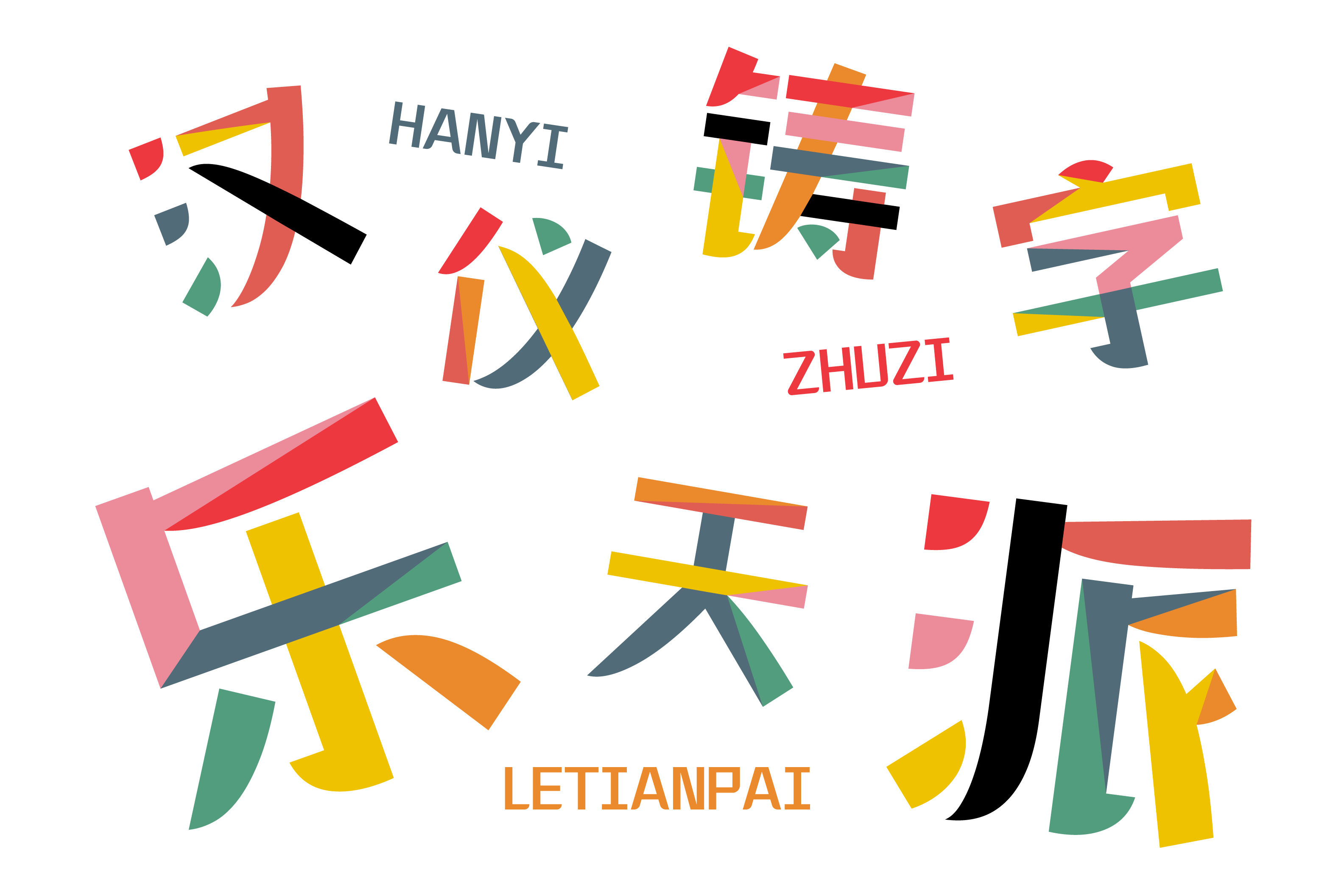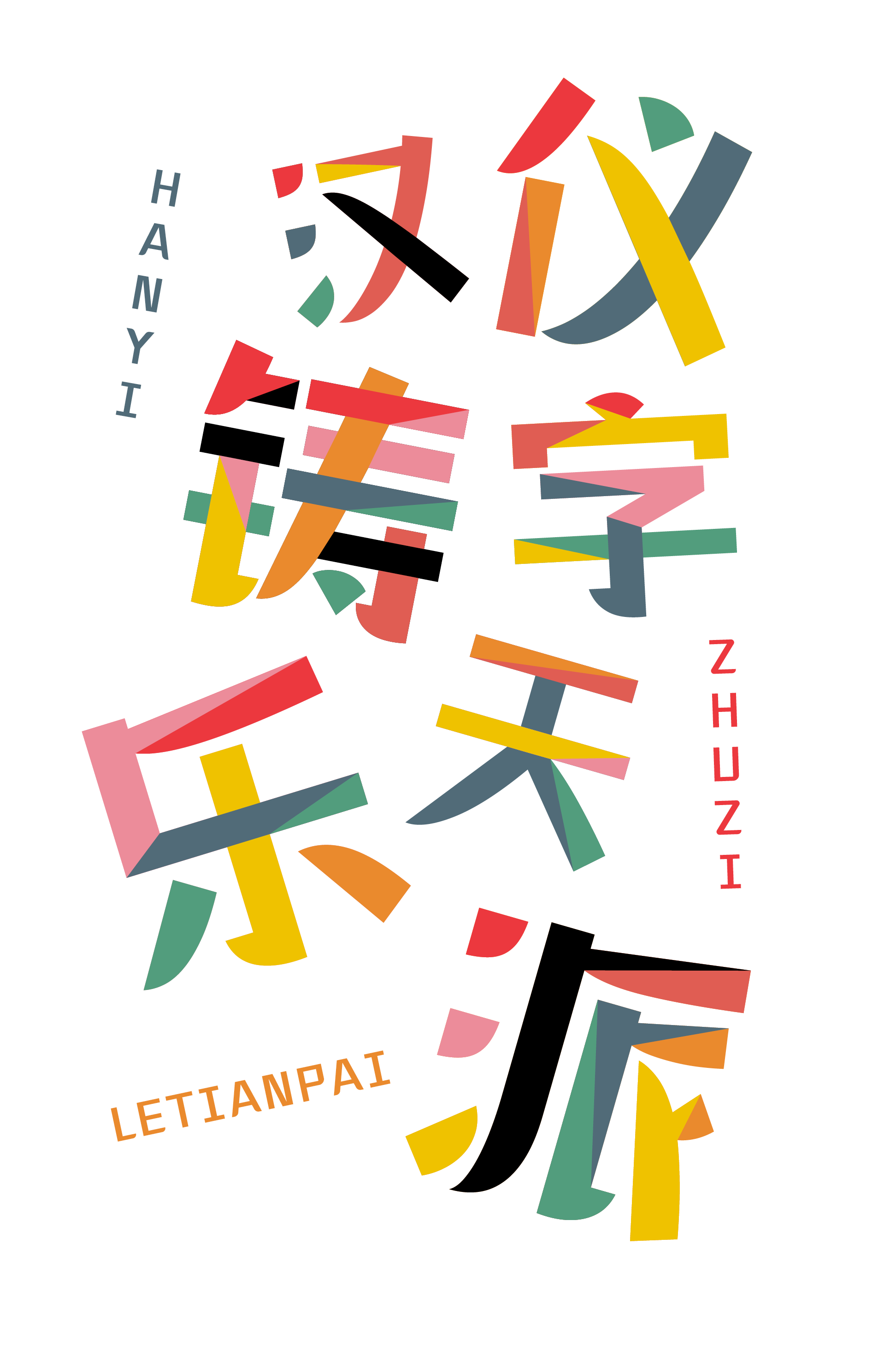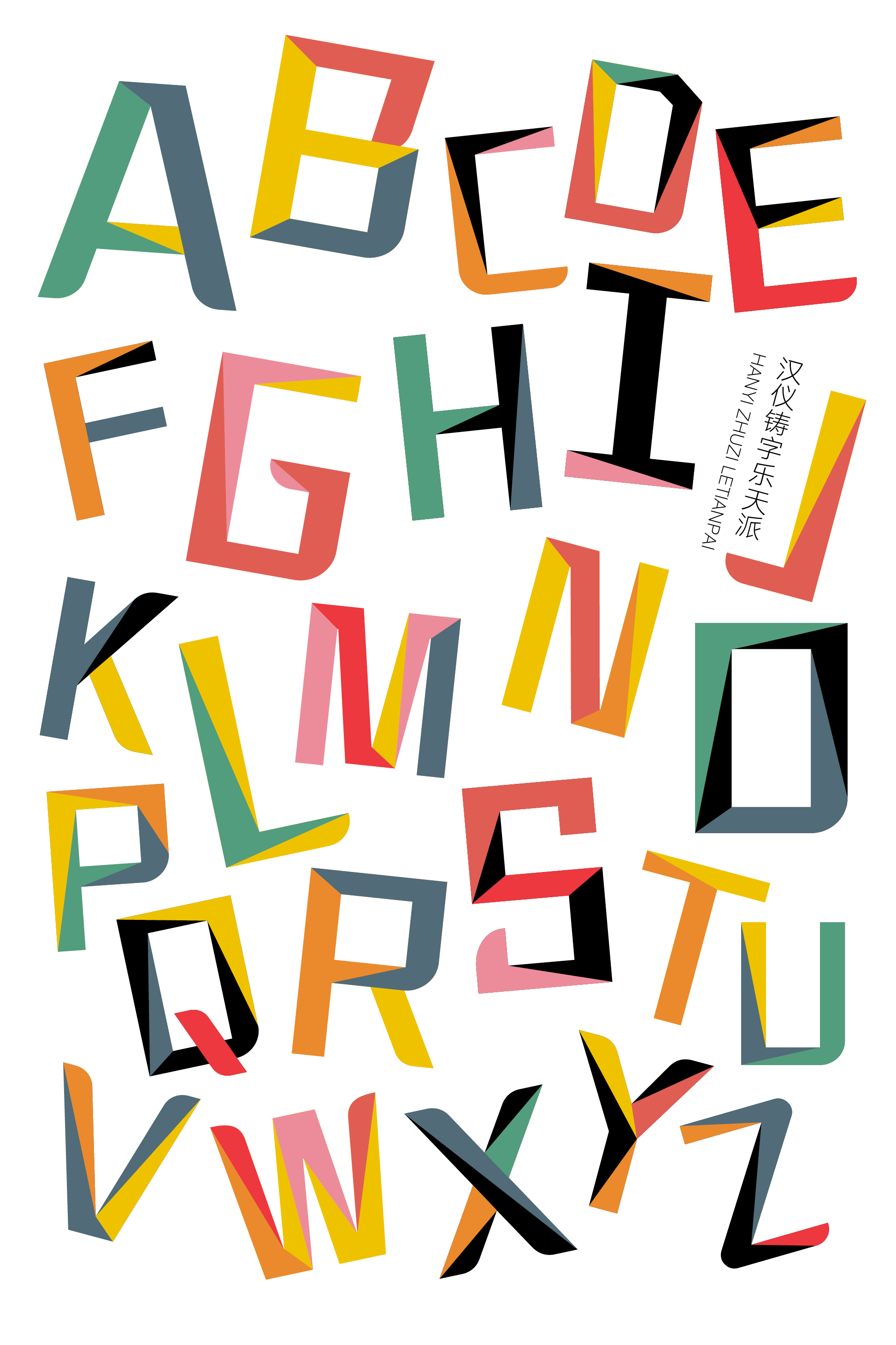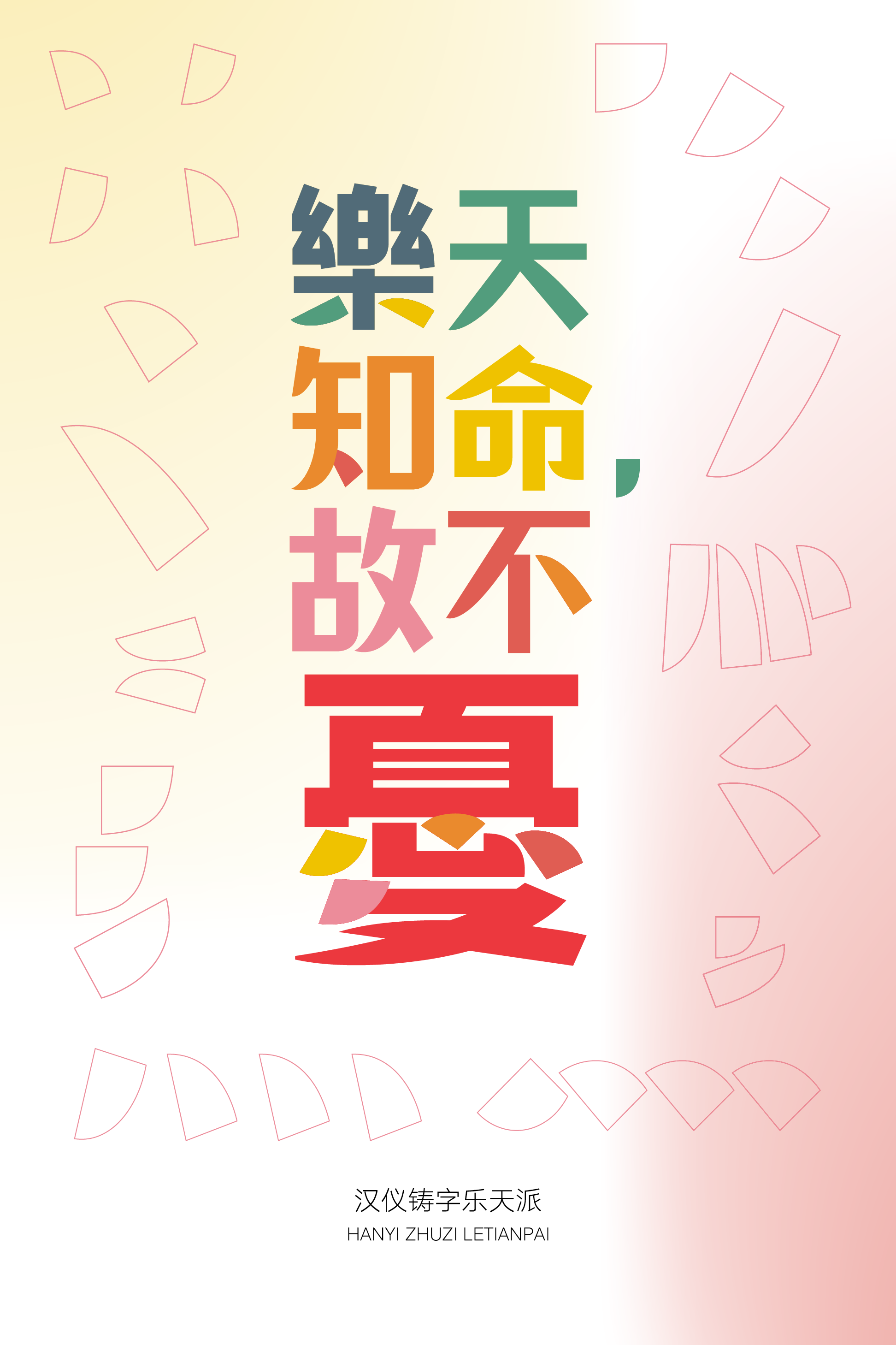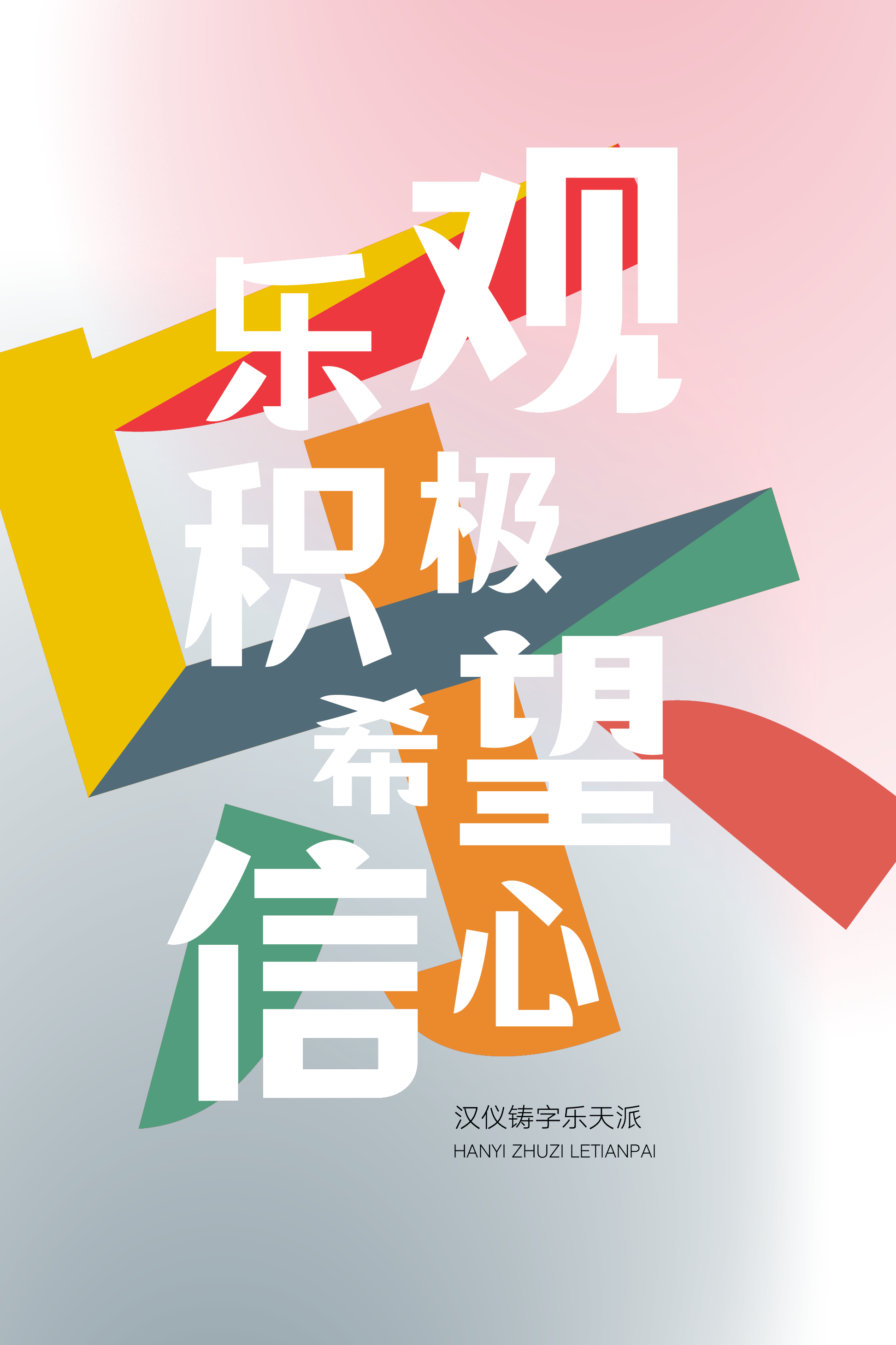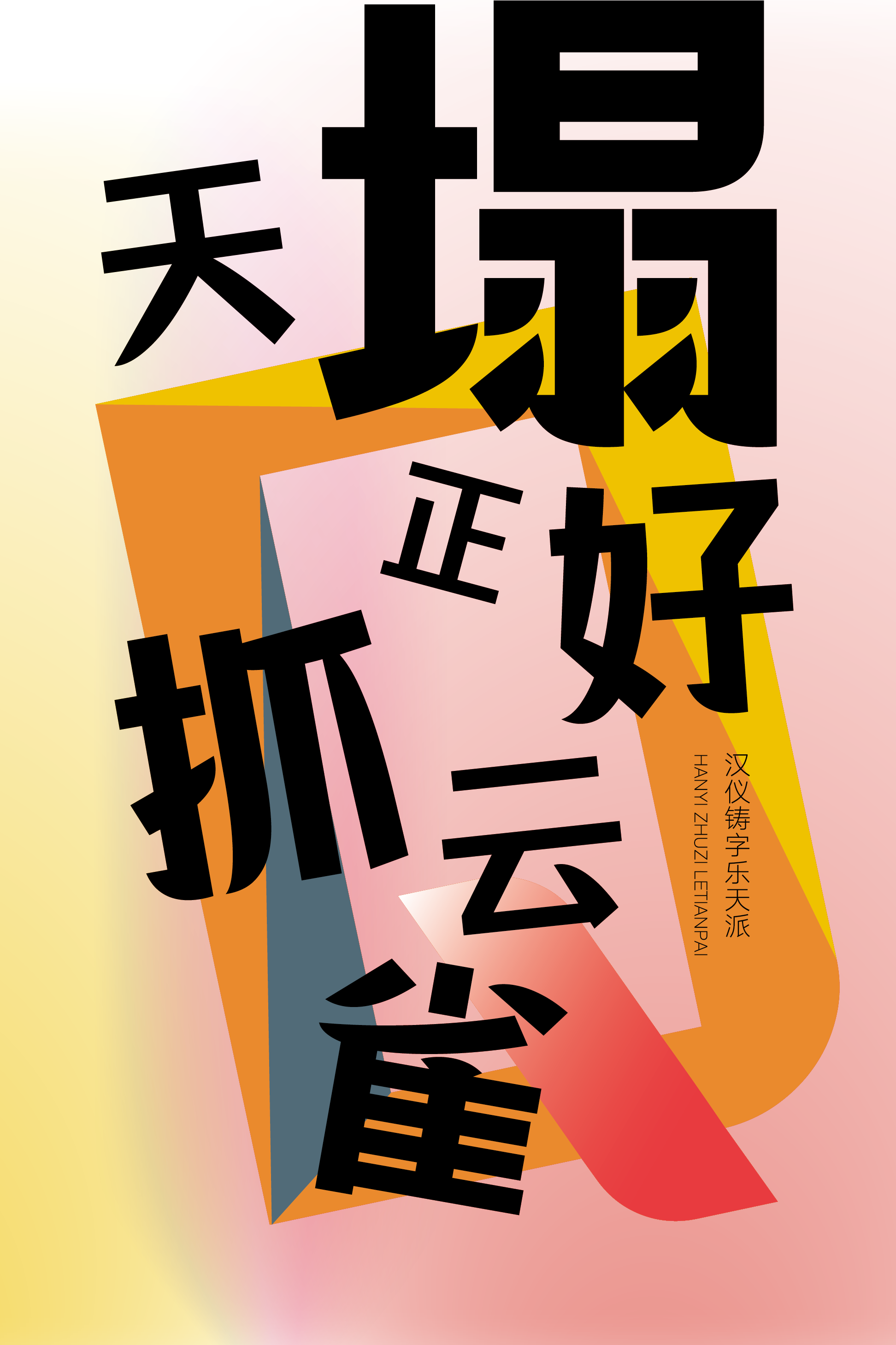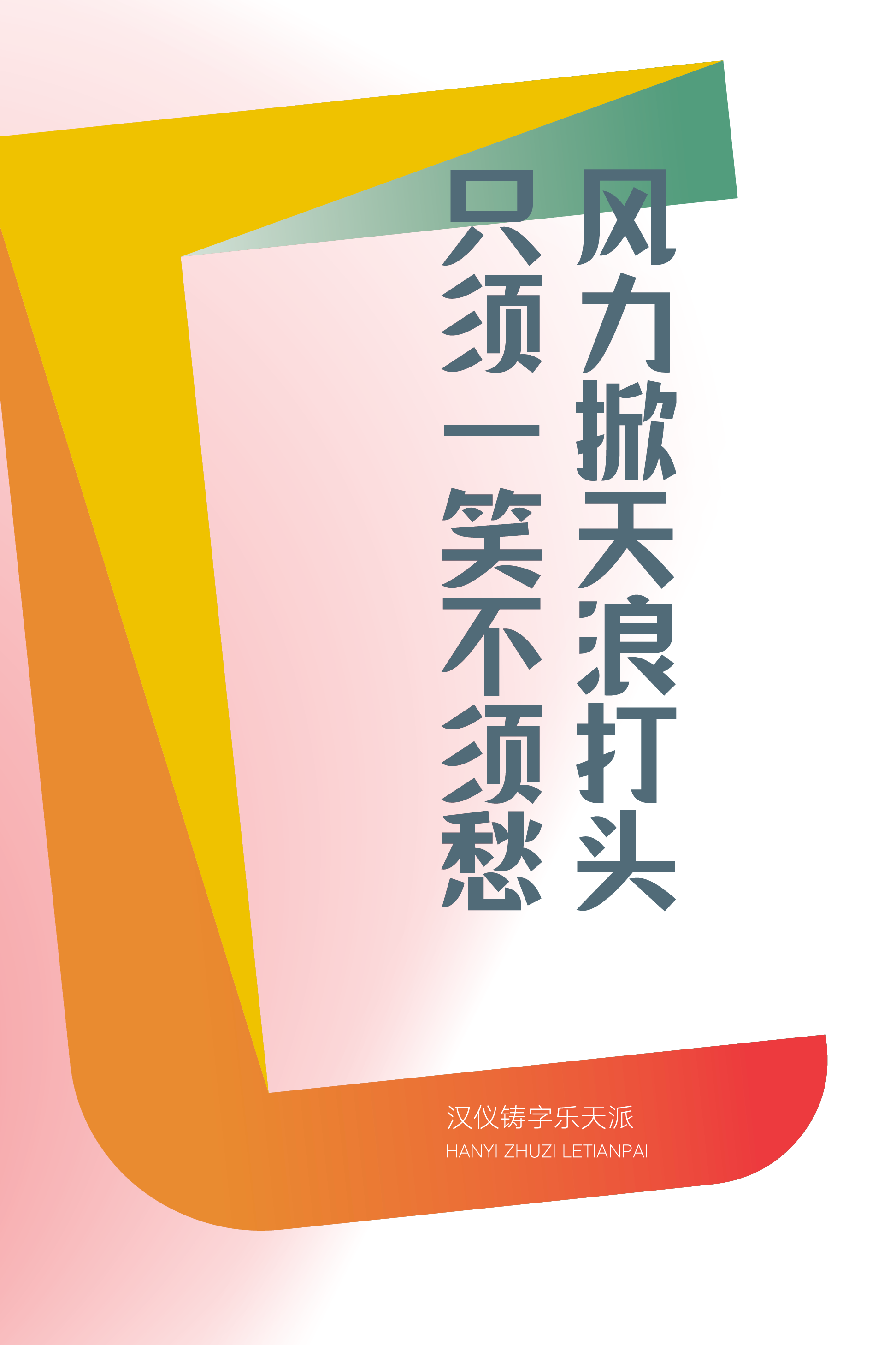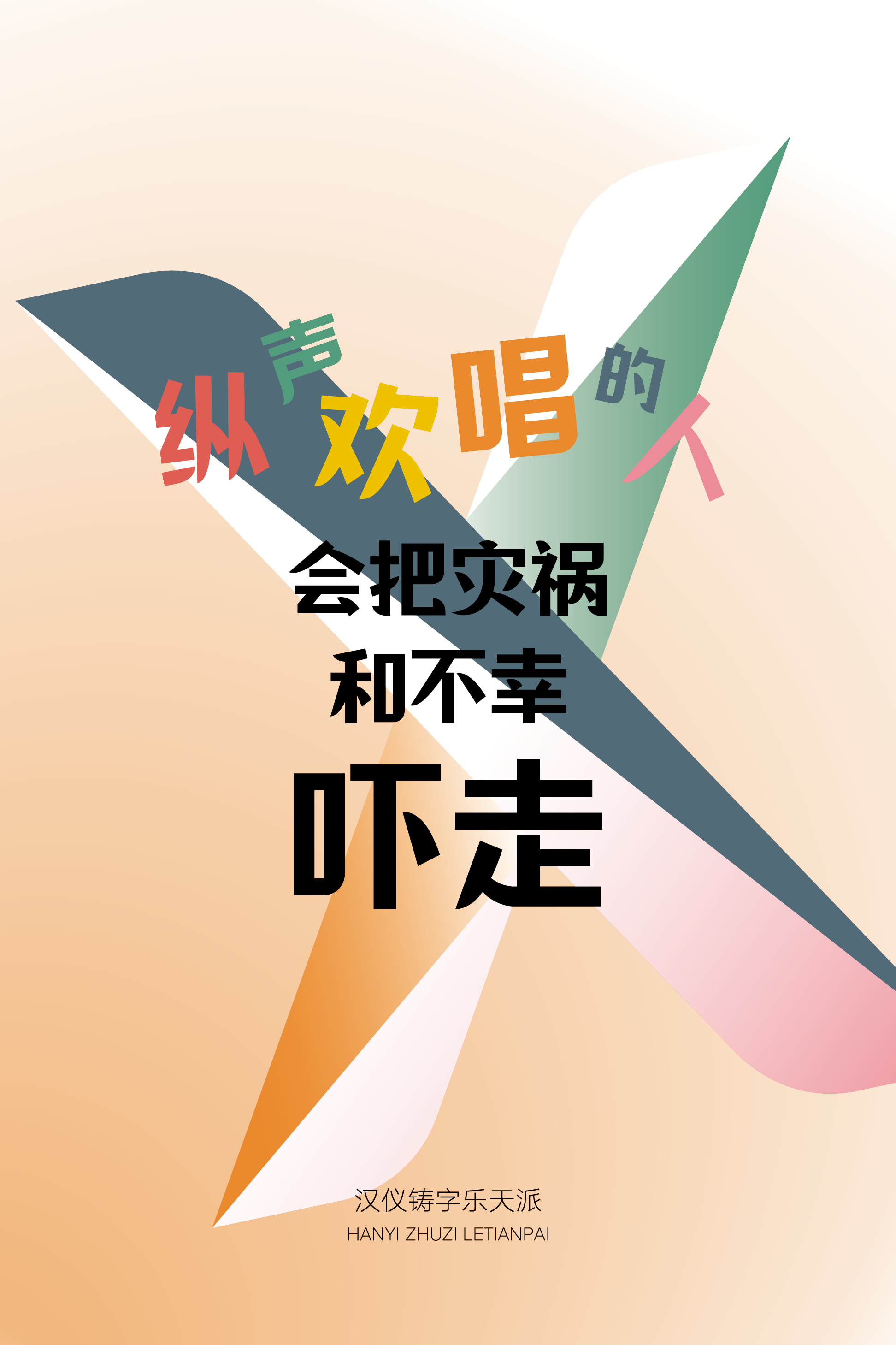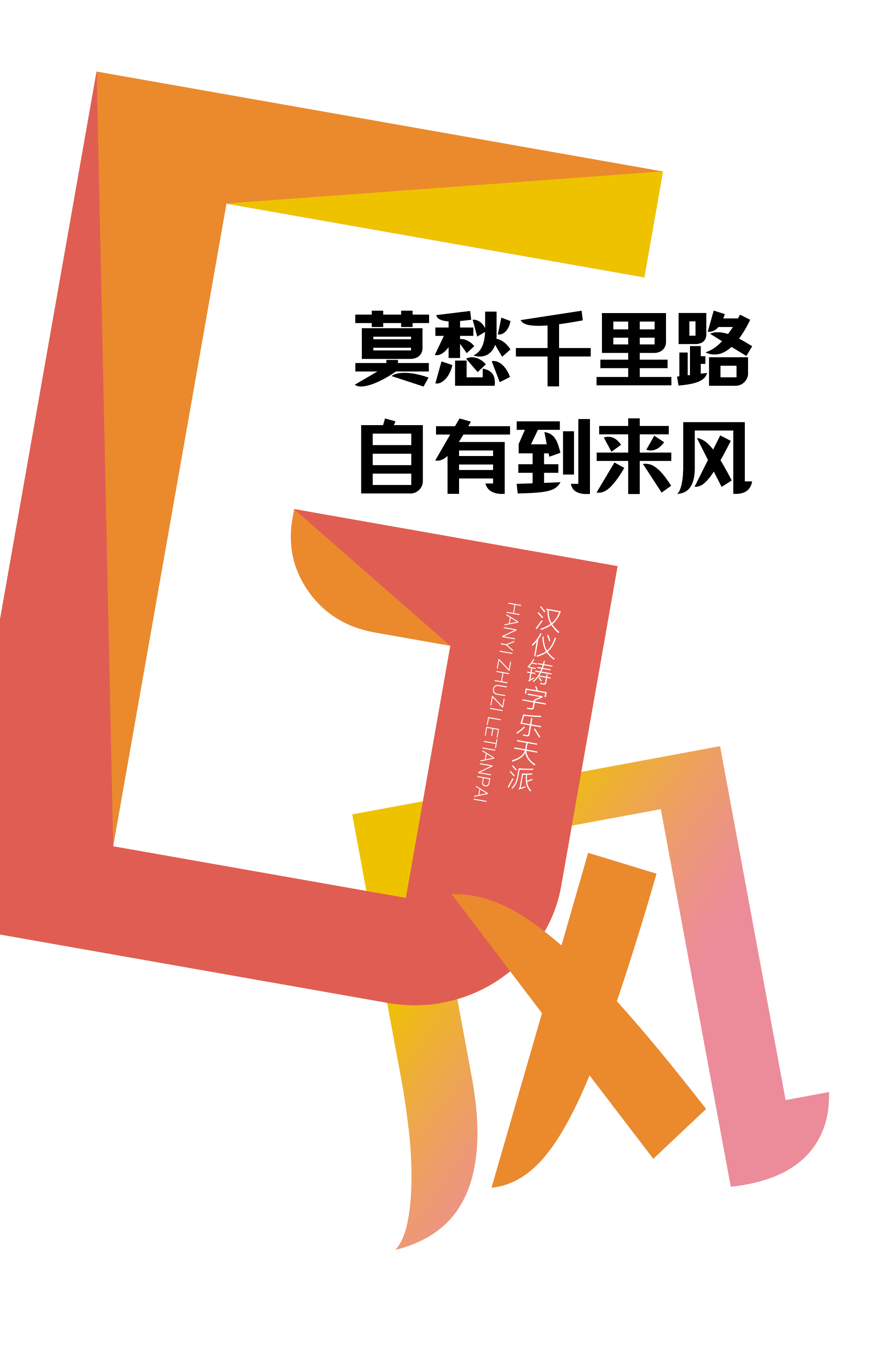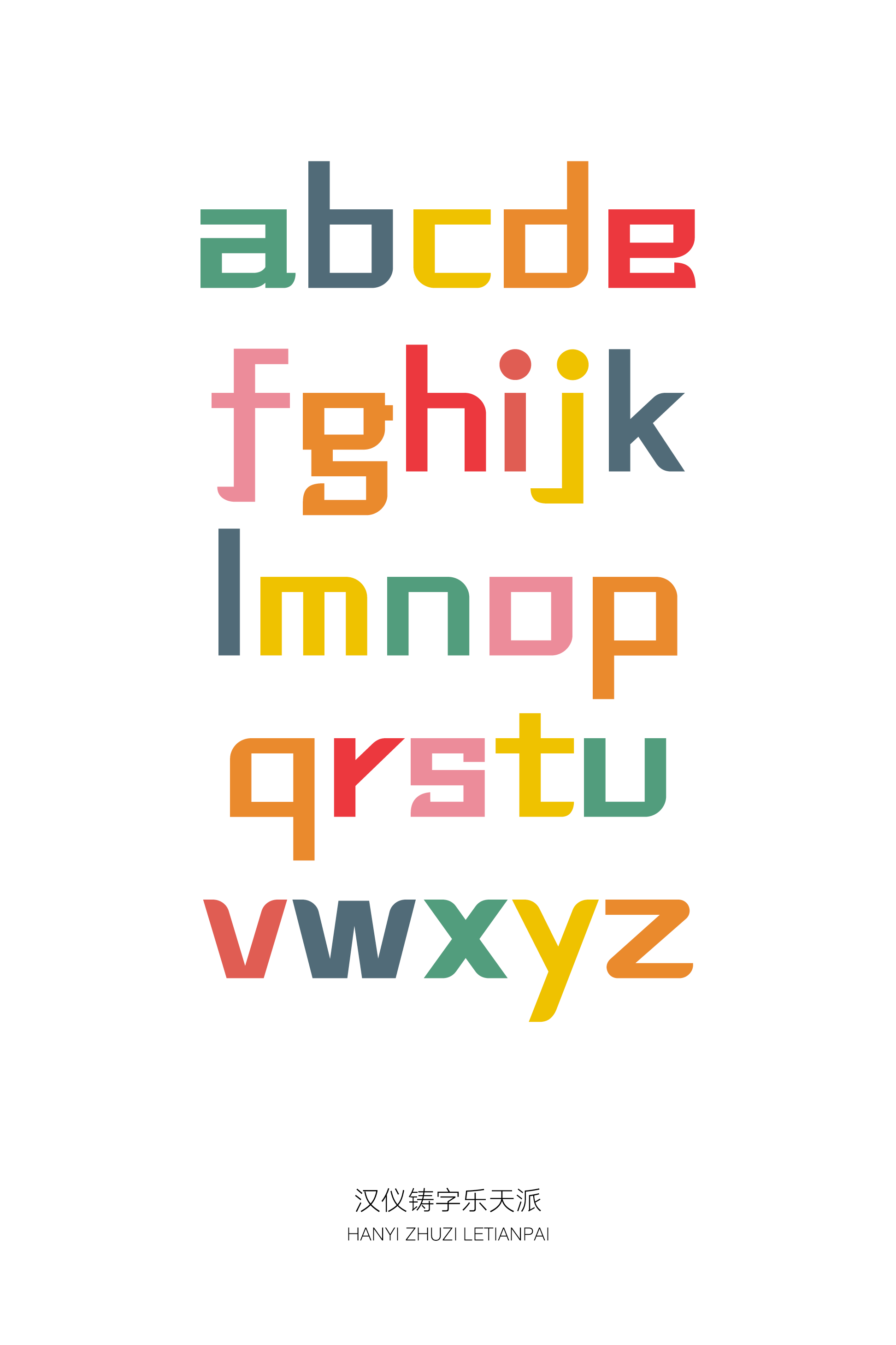
汉仪铸字乐天派字体介绍,汉仪铸字乐天派设计灵感
汉仪铸字乐天派 | 整体特点
“汉仪铸字乐天派” 是汉仪旗下的 “铸字社工作室” 打造的一款创意型设计字体。这是一款风格轻松活泼的标题字,适用于少量字数的排版设计。
汉仪铸字乐天派 | 字形特点
“汉仪铸字乐天派” 的整体字形趋向正方形,字体重心略微偏上,空间结构均衡疏朗,使得字体在整齐中不失开朗、稳重中不失活泼。
汉仪铸字乐天派 | 笔画特点
“汉仪铸字乐天派” 的横画与竖画均由矩形构成,横画比竖画微细,让字体在表达简洁疏朗的语境下有更舒适的视觉体验。
“汉仪铸字乐天派” 在一些笔画细节上以饱满的弧线修饰,使字体的形式表达更加温和,柔中有方,刚柔并济。
“汉仪铸字乐天派” 的点笔画形态丰富多样。虽然都是由右侧放大度数的圆弧曲线构成,但是会根据空间位置不同有大小和角度上的变化。
汉仪铸字乐天派 | 中西文匹配
“汉仪铸字乐天派” 的西文字母有着和中文一样的笔画特点,中西文搭配使用十分和谐。
设计师对西文字母做出了差异性处理,如大写 “O”右上为直角,大写“D”做了切线处理,这样可以避免在混排时出现不易识别的情况。
汉仪铸字乐天派 | 排版效果
汉仪铸字乐天派 | 海报样张